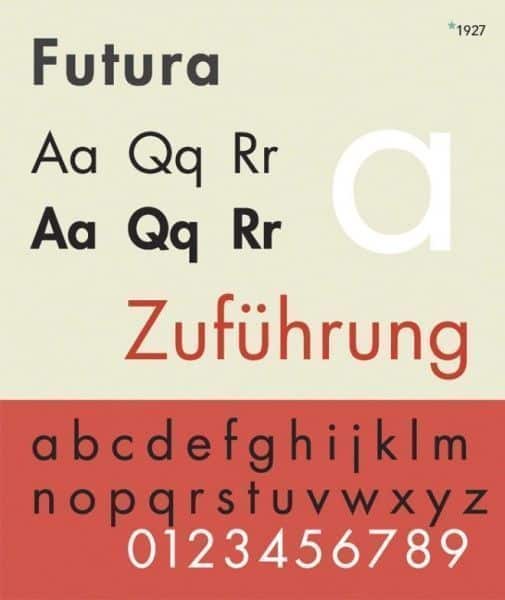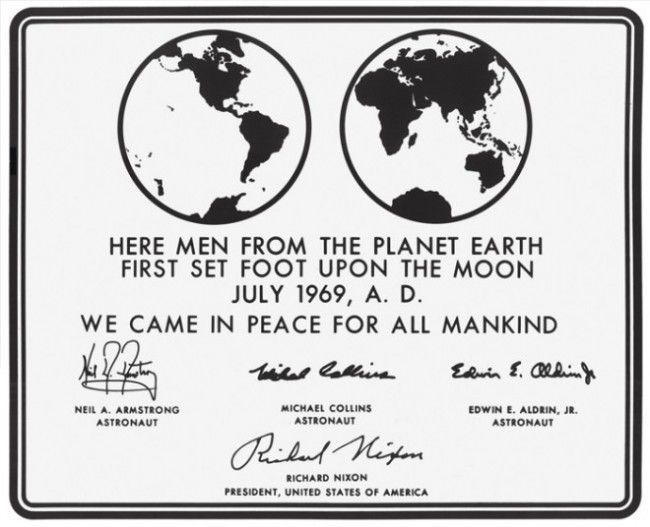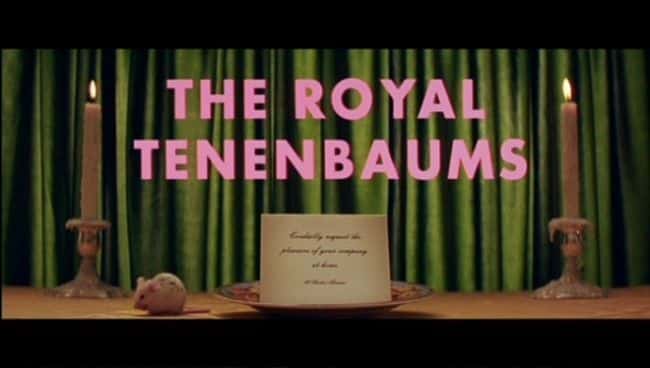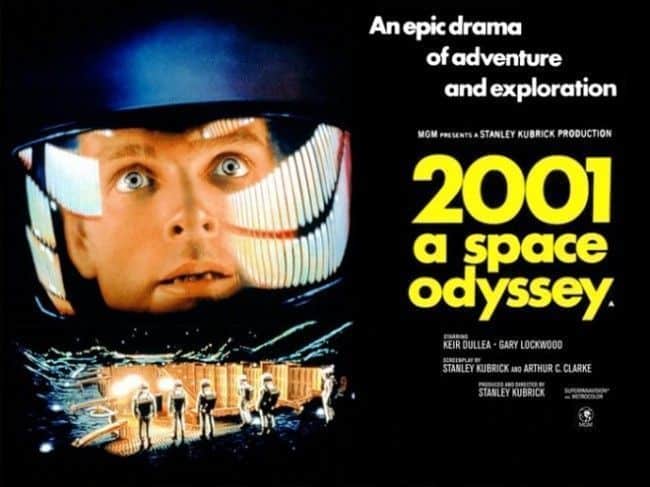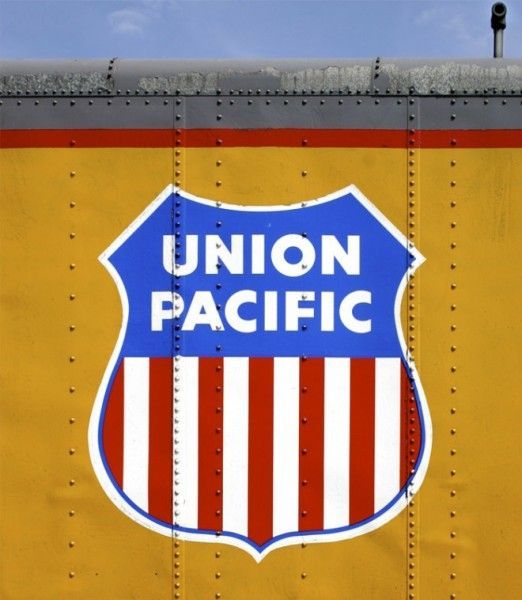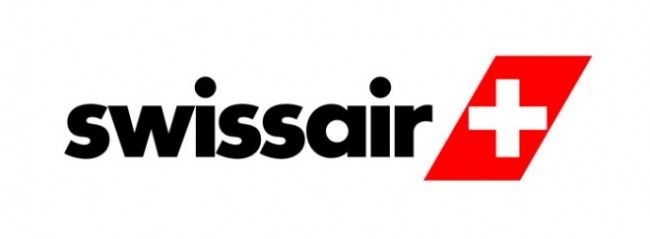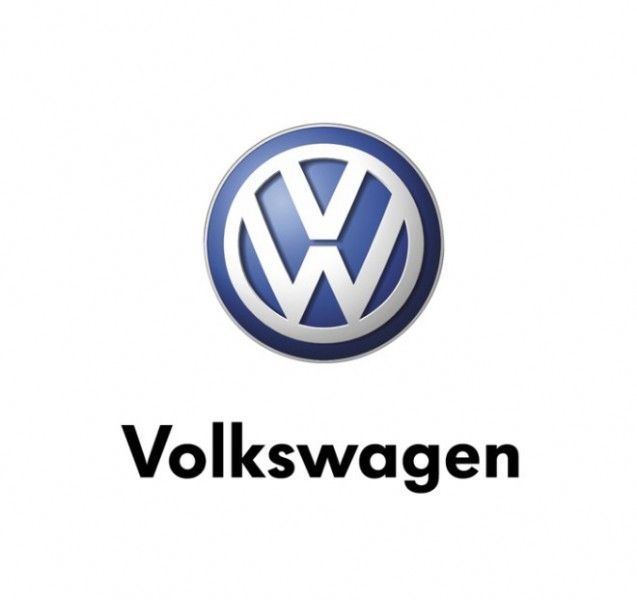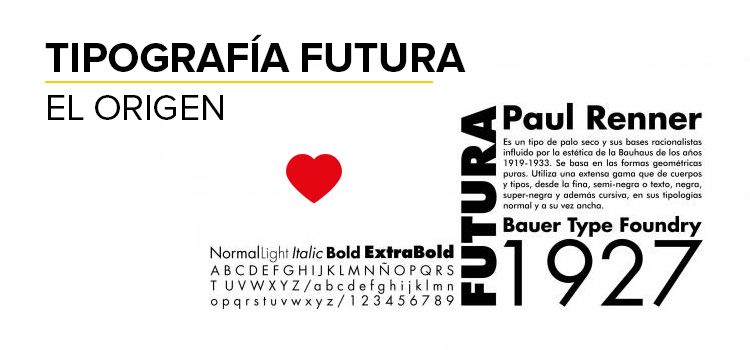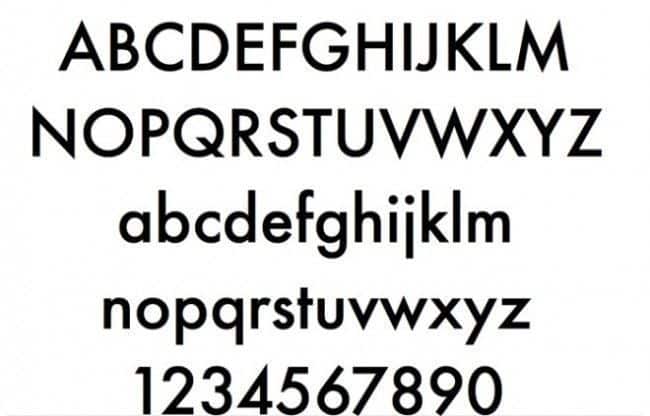
Origen de la tipografía Futura
Un repaso a la historia de la tipografía Futura, creada en 1927 por la fundición Bauer y Paul Renner.
En 1927 la fundición Bauer lanzó al mercado la tipografía Futura, tipografía diseñada por el alemán Paul Renner entre 1924 y 1926. Se trata de una tipografía geométrica, de palo seco, neutra y muy funcional.
Pese a no pertenecer a la Bauhaus, Renner aplicó sus principios básicos de racionalismo y funcionalidad a su trabajo. La tipografía Futura se construye a partir de formas geométricas simples (cuadrados, círculos y triángulos), posee largos ascendentes y descendientes, así como una apariencia limpia y clara. Sentó las bases de la nueva tipografía. Su uso es apropiado para anuncios, carteles, rótulos, cubiertas de libros…
La Futura ha influido en importantes trabajos tipográficos posteriores como la Avenir de Adrian Frutiger o la Avant Garde de Herb Lubalin. Fue empleada en populares identidades corporativas como Volkswagen, Swissair o Union Pacific. Stanley Kubrick y Wes Anderson las utilizaron para los títulos de crédito y carteles de varias de sus películas y con ella se grabó la placa que Armstrong y Aldrin dejaron en la luna.